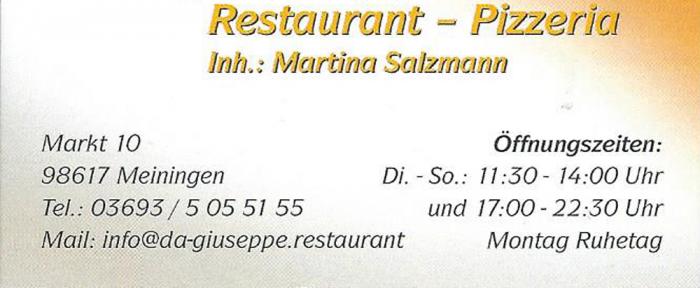
Suche Schrift für Pizzeria
ich soll für einen Kunden eine Schriftart suchen.
Als einzigsten Anhaltspunkt hab ich diese eingescannte Visitenkarte.
Welche Schrift ist das? Müsste eigentlich oben die selbe Schriftart wie unten sein - nur eben etwas fetter.
sieht schon mal nicht schlecht aus. Mal schauen, was der Kunde dazu sagt.